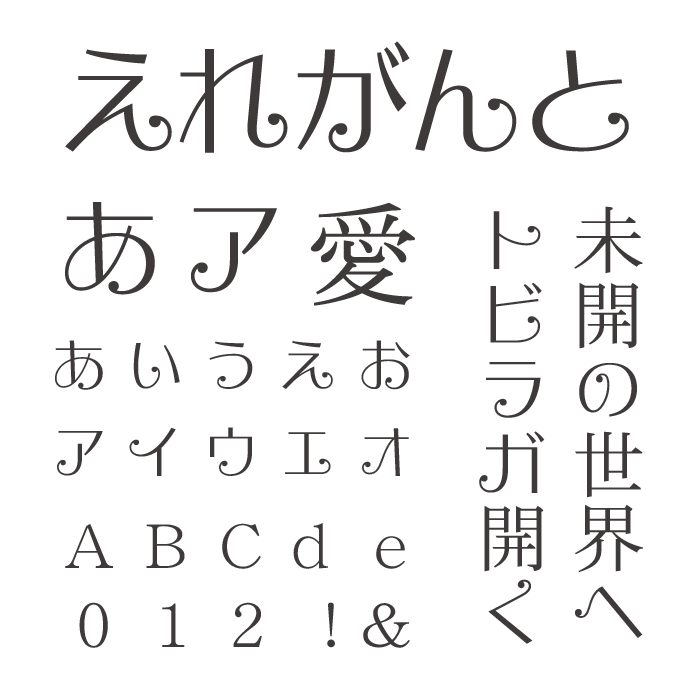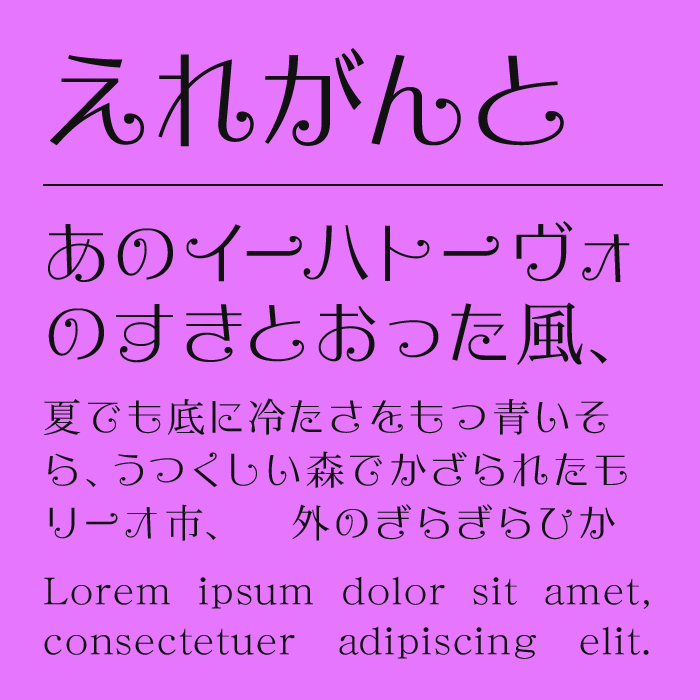
えれがんとは、細い線とゆったりした曲線が印象的な、名前の通り上品な雰囲気を持ったデザインフォントです。
ひらがなの払いには小さなカールや丸みが入り、明朝体とも手書き文字とも少し違う、装飾文字らしい華やかさがあります。
線は細めですが、文字の形にはしっかり個性があるため、短いタイトルやブランド名などに使うとよく映えます。
コスメやアクセサリー、ウェディング、カフェのメニュー、女性向けのWebデザインなど、少しクラシカルな空気を加えたい場面にもぴったりです。日本語と欧文を並べても雰囲気が揃いやすく、静かにきれいに見せたいデザインで使いやすいフォントです。